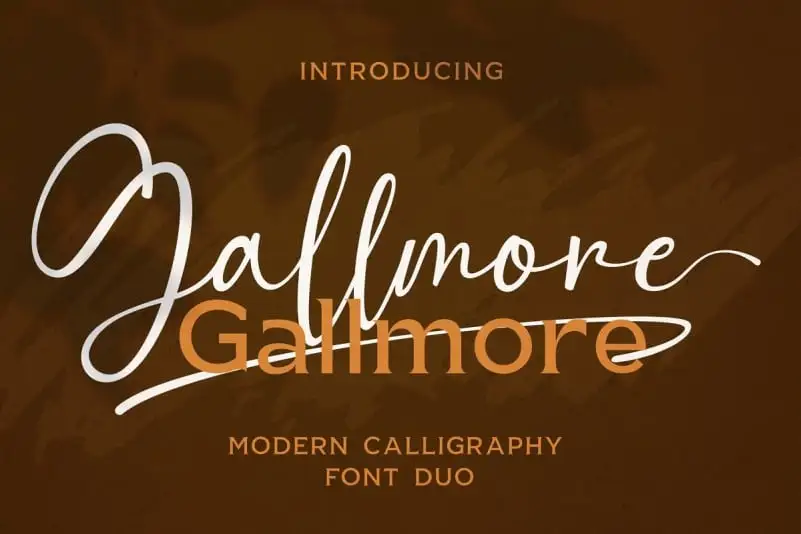
Gallmore Font Duo é uma ótima escolha para designers que buscam estilo e elegância em seus projetos digitais. Conhecida por sua combinação singular de letra cursiva com tipografia serifada, esta fonte oferece um equilíbrio perfeito entre personalidade e formalidade. Gallore Font Duo foi cuidadosamente criada para garantir que cada letra exiba uma beleza única e profunda, fazendo seu texto se destacar em qualquer ambiente de design. Com mais de 227 glifos incluídos (incluindo 30 alternativas com swashes), este conjunto de fontes oferece um amplo espectro para personalizar seus projetos. Além disso, a Gallore Font Duo vem com uma extensa gama de caracteres latinos, permitindo que você atenda a necessidades linguísticas mais complexas. Estamos certamente que esta combinação única de elegância e versatilidade tornará o Gallmore Font Duo uma escolha valiosa para projetos como cartões de convite, marcas de marca, anúncios e design de outdoors. O fato de ser PUA codificado também garante que todos os caracteres sejam acessíveis por meio do Character Map, Font Book ou qualquer gerenciador de fontes de sua escolha. Esta fonte é perfeita para quem busca algo que destaque seu trabalho sem perder a elegância e sofisticação. Com Gallmore Font Duo, seus designs ficarão ainda mais profissionais e personalizados.